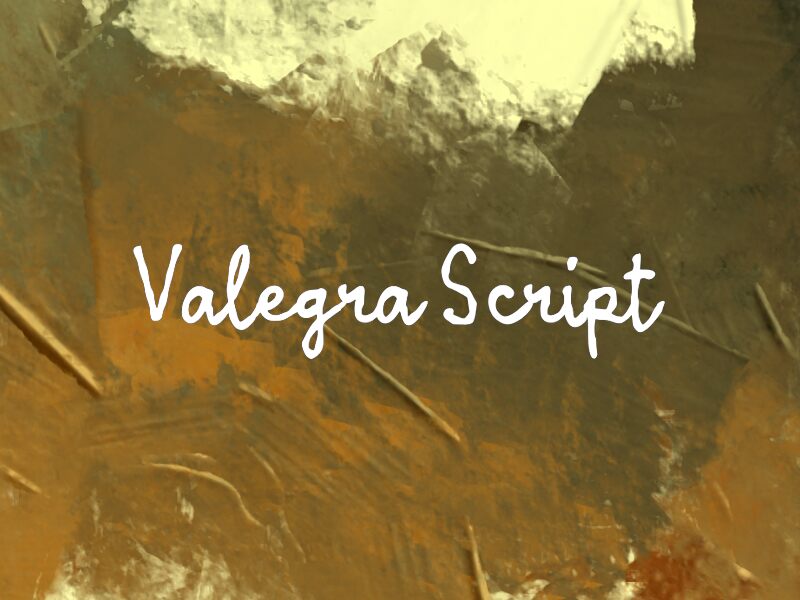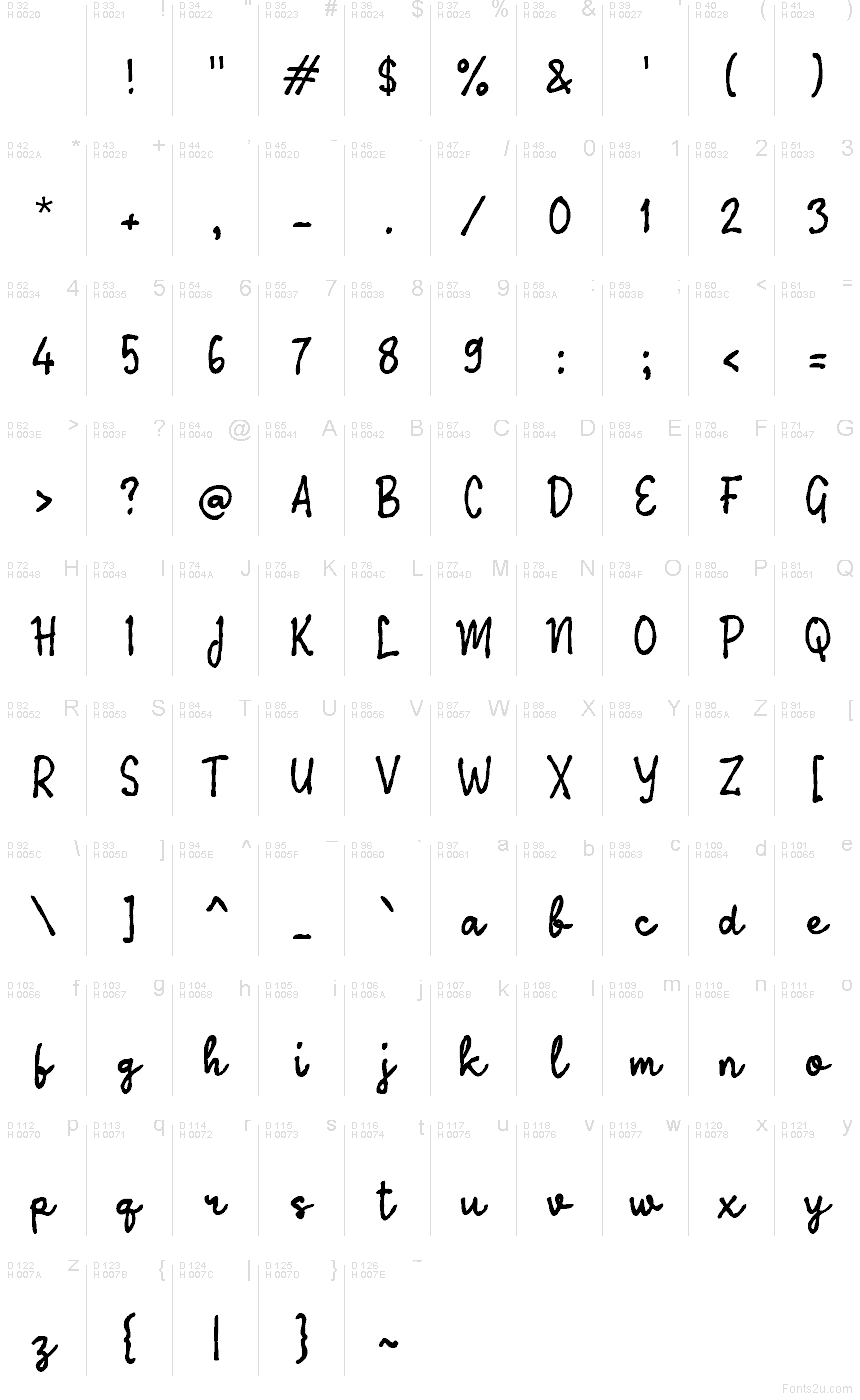
Valegra Script
Valegra Script di Wep è un font scritto a mano gratuito che richiama la spontaneità e il calore di una scritta a pennarello. Le lettere alternano tratti ampi a occhielli stretti, con ascendenti slanciate e un ritmo leggermente irregolare che conferisce un aspetto autentico, lontano da ogni formalismo o eccessiva perfezione.
È perfetto per il branding di piccoli negozi, menu di bar, packaging, biglietti d'auguri e post sui social, dove un font gratuito dal tocco umano risulta più naturale di una calligrafia rigorosa. Usalo per titoli brevi, copertine o logotipi, specialmente quando vuoi che le linee lunghe e sinuose facciano da protagoniste nel design.